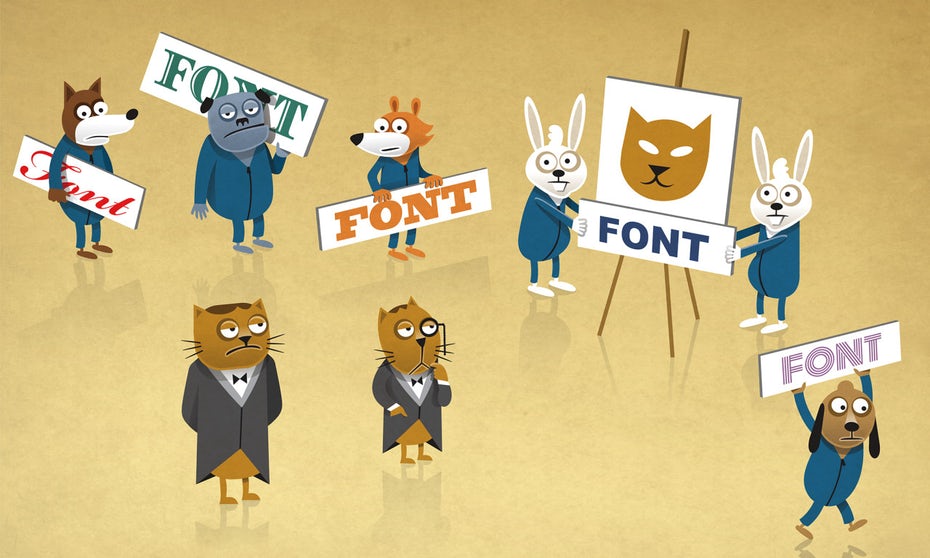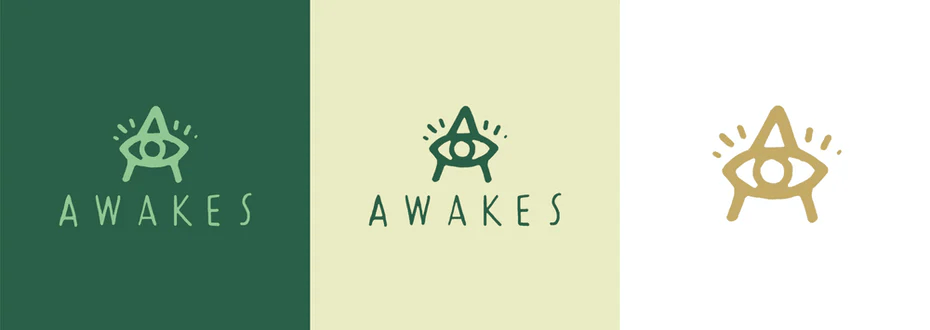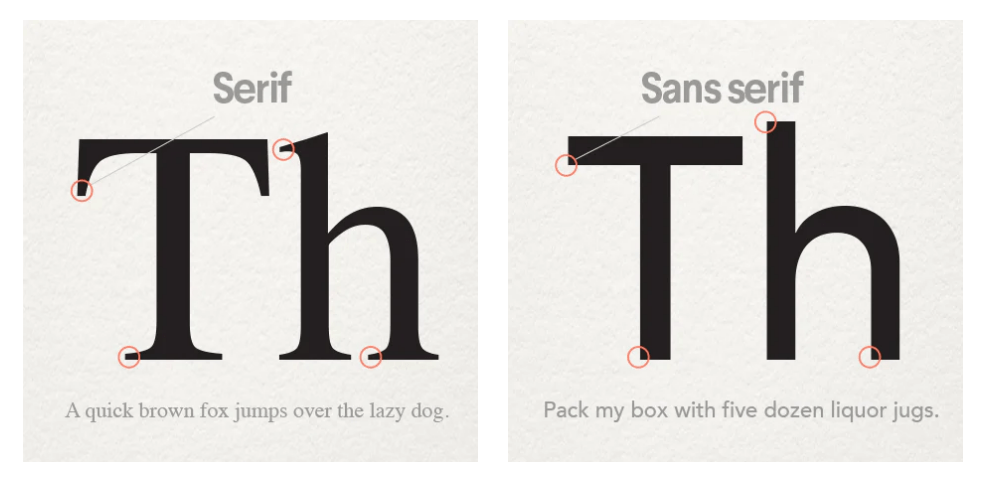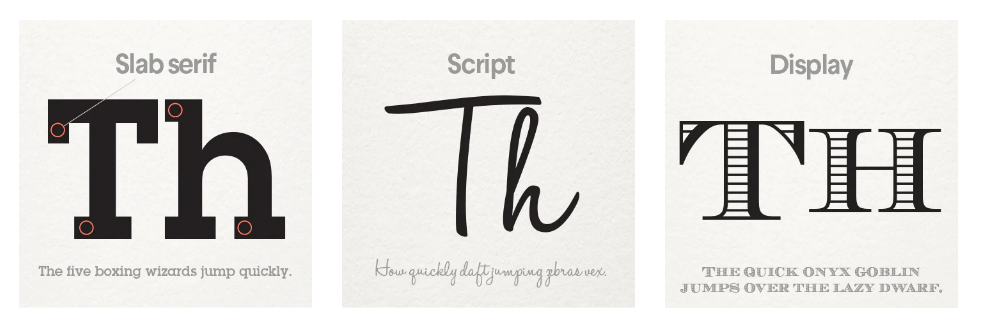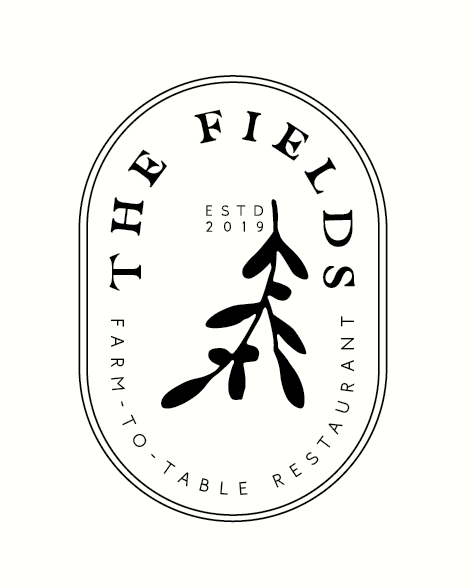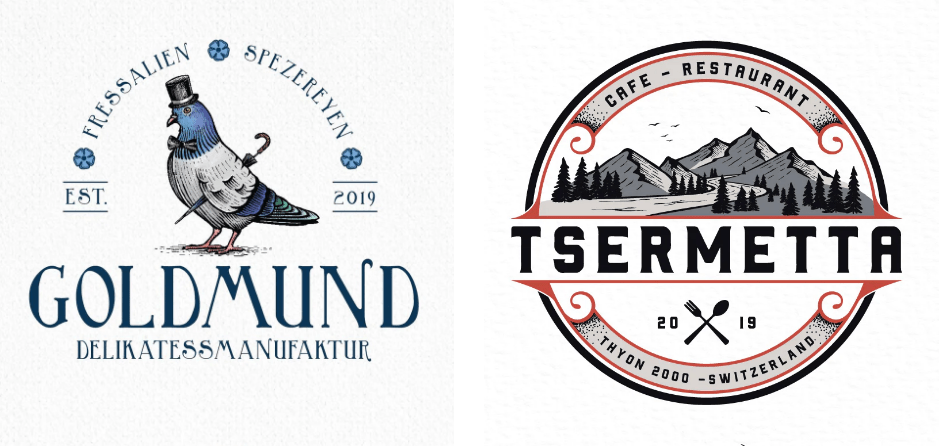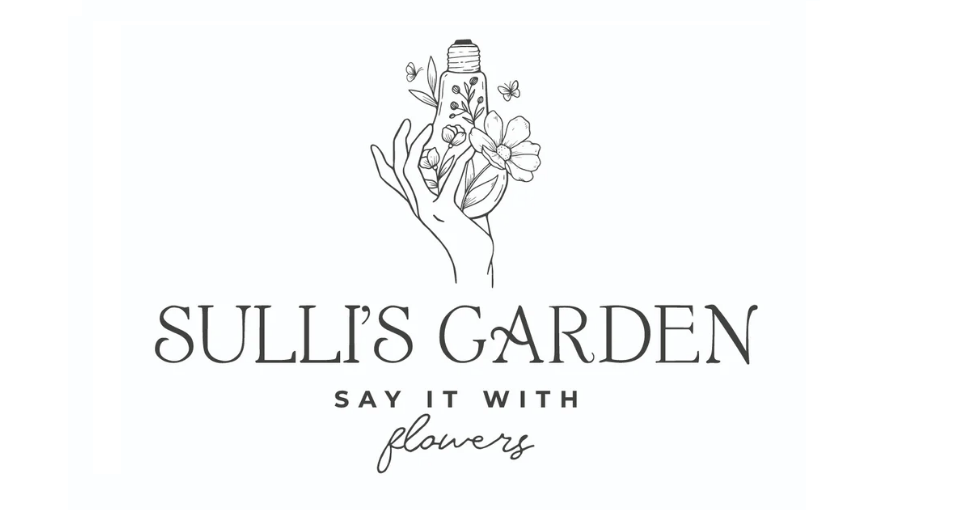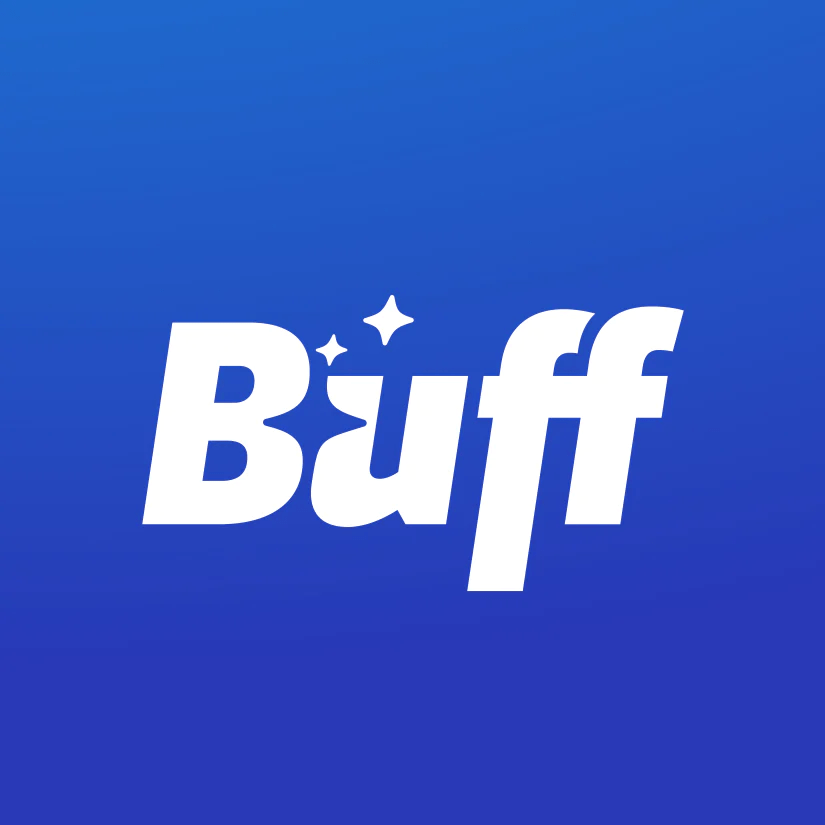
Khi nghĩ đến logo, thứ đầu tiên xuất hiện trong tâm trí bạn là gì? Phải chăng là những yếu tố  đồ hoạ hoặc hình ảnh nào đó? Liệu các designer nên chọn kiểu chữ có chân hay không chân, cứng rắn hay mềm mại cho những sản phẩm thiết kế của họ?
Để cho ra đời được một thành phẩm logo đúng nghĩa, một người designer không chỉ phải  thể hiện hình ảnh, thông điệp của thương hiệu vào trong một thiết kế đồ họa nhỏ bé, mà họ còn phải tìm ra những phông chữ phù hợp để truyền tải thông tin về thương hiệu một cách tốt nhất. Việc đó càng khiến các designer phải hao tâm tổn sức rất nhiều để tìm ra đâu mới là là font chữ “chân ái” của thương hiệu mà họ đang thiết kế.
Chọn font chữ như thế nào mới phù hợp với logo thương hiệu?
Điểm danh các loại font chữ cơ bản và mối liên kết của nó với cá tính thương hiệu
Trong thế giới của font chữ, bạn sẽ bắt gặp hàng triệu những loại font chữ khác nhau. Tuy nhiên mỗi loại font đều có những thuộc tính và bản tính riêng biệt. Nhưng bạn có biết font chữ như thế nào thì phù hợp với trang web, còn loại font ra sao thì phù hợp với tài liệu quảng cáo và các sản phẩm in, email, danh thiếp?
Các font chữ khác nhau sẽ sở hữu i những thuộc tính khác nhau và đại diện cho những tính cách riêng biệt. Logo và nét chữ trên đó phần nào sẽ giúp người nhìn hiểu được về tính chất của doanh nghiệp hoặc mặt hàng mà doanh nghiệp đó đang  kinh doanh. Điều đó đồng nghĩa với việc logo sẽ là nơi đầu tiên truyền tải thông điệp thương hiệu đến khách hàng. Do đó, cách font chữ được sử dụng trong việc thiết kế logo cực kỳ quan trọng, chúng cần được lựa chọn kỹ càng và mang tính lâu dài.
Tựu trung lại, chúng ta có những font chữ cơ bản và phổ biến sau đây, nhưng hãy đọc tiếp phần sau để hiểu sâu hơn mối liên hệ mà mỗi loại phông chữ sẽ gợi lên ở khách hàng tiềm năng.
– Serif: Sự cổ điển, sang trọng, truyền thống.
– Sans-Serif: Sự hiện đại, sạch sẽ, hơi hướng hình học, đơn giản.
– Slab Serifs: Sự cổ điển, mộc mạc, nam tính.
– Script: Sự tinh tế, nữ tính, có tính trang trí ứng dụng, thanh lịch.
– Handwritten: Dấu ấn cá nhân, giản dị, gần gũi.
– Display: Sự vui mắt, mới lạ
Độ dày nét chữ và khả năng ứng dụng
Để đánh giá một font chữ có phù hợp với thương hiệu hay không, ngoài yếu tố thẩm mỹ và sự kết nối với các tính cách như đã nêu trên, người thiết kế còn  phải xem xét đến độ dày của nét chữ và khả năng linh hoạt của chúng khi ứng dụng trên nhiều ấn phẩm khác nhau.
Khi đã chọn ra được  danh sách  các phông chữ phù hợp , bạn đã có thể thu hẹp phạm vi lựa chọn khi đã có các đặc điểm về phong cách và thuộc tính của thương hiệu . Hầu hết các font chữ đều đi theo một loạt biến thể về cách đi nét và độ dày nét, từ mảnh đến dày, từ bề mặt chữ có màu đến chữ chỉ có viền nét.
Thông thường những font chữ nét dày dặn có thể sẽ đẹp đối với thương hiệu có tên ngắn gọn, nhưng sẽ trông nặng nề và thô kệch khi áp dụng cho những cái tên dài hơn. Còn font chữ mảnh mai sẽ phù hợp trên những tấm biển quảng cáo cỡ đại, nhưng lại sẽ có thể “vô hình” trên một chiếc danh thiếp được in với kích cỡ nhỏ. Hơn nữa, nếu xét ở góc độ kết nối với tính cách, trong khi nét dày đại diện cho sự quyết đoán, mạnh mẽ thì nét mỏng lại biểu hiện sự tinh tế, nhẹ nhàng.
Nói tóm lại, nếu bạn muốn thiết kế một chiếc logo sang trọng, hãy cân nhắc những font chữ nét mảnh mang cảm giác tinh tế, trường hợp này nếu dùng phông chữ nét dày sẽ khiến thiết kế trở nên bảo thủ và nặng nề.
Bên cạnh đó, người thiết kế cũng có thể tạo điểm nhấn cho logo bằng việc phá cách với các font chữ vốn đã quen thuộc. Thậm chí, họ có thể kết hợp nhiều hơn một font trên cùng một chiếc logo như thiết kế của nhà hàng The Fields dưới đây. Sự kết hợp giữa nét chữ cổ điển, mềm mại phía trên với nét chữ dứt khoát, hiện đại phía dưới đã tạo nên cảm quan vô cùng hài hòa và thú vị.
Thiết kế logo của một nhà hàng với phông chữ serif viết tay. Minh họa bởi EWM Designs.
Trong thiết kế logo của nhà hàng The Fields, chữ “E” trong chữ “The Fields” được thể hiện bằng font Serifs chính là điểm nhấn khác biệt. Bên cạnh đó, mật độ xuất hiện vừa phải (chữ cái “E” chỉ xuất hiện hai lần trong logo) cũng là yếu tố gây thích thú cho người xem, nếu chữ “E” xuất hiện nhiều hơn hai lần có thể sẽ không còn gây được ấn tượng.
Tóm lại, trước khi lựa chọn font chữ cho thiết kế logo, hãy cân nhắc mọi khía cạnh liên quan đến thương hiệu. Nhờ vậy bạn mới có thể sáng tạo được một thiết kế vừa thỏa mãn khách hàng, vừa đạt được kỳ vọng của bản thân.
Sự tương hợp giữa font chữ và ngành hàng
Khi cân nhắc lựa chọn font chữ cho logo, điều quan trọng không chỉ là bạn muốn logo trông như thế nào mà còn là bạn muốn nó  được cảm nhận như thế nào. Liệu logo có cần biểu đạt một hàm ý lịch sử, hay chỉ cần mang đến cảm giác thích thú và hiện đại? Điều này cần bạn phải có hiểu biết thực tế và cực kỳ sâu sắc về ngành lẫn thương hiệu đó.
Kiểu chữ gợi cảm giác chân chất, mộc mạc có thể phù hợp với logo của một cửa hàng cơ khí nhưng sẽ hoàn toàn lạc lõng trên logo của một công ty phần mềm. Một kiểu chữ tạo sự rung cảm thô mộc có thể phù hợp với cửa hàng cơ khí nhưng sẽ trở nên lạc lõng trên logo của công ty phần mềm. Vì vậy trước khi đặt bút phác thảo một logo bất kì, người thiết kế cần nghiên cứu những mong đợi, sở thích, tính cách chung của người tiêu dùng trong ngành hàng đó để tìm kiểu chữ phù hợp.
Chọn font chữ như thế nào mới phù hợp với logo thương hiệu?
Bên cạnh đó, hãy cẩn thận với những font chữ quá phổ biến, ví dụ như kiểu chữ Serifs (không chân) theo dạng cổ điển vì nó đã quá “nhẵn mặt” với các hãng bia đến nỗi chúng chẳng còn gì mới lạ với người tiêu dùng. Còn đối với ngành công nghệ, phông chữ Sans-Serifs (có chân) cũng khiến cho các logo trở nên nhạt nhòa trong hàng loạt thiết kế tương tự.
Chính vì thế mà đôi khi sử dụng những font chữ đặc trưng, dễ nhận biết của ngành lại mang tác dụng phụ, khiến logo của  bạn trở nên chìm nghỉm giữa các đối thủ khác. Do đó, kết quả cuối cùng của việc thiết kế logo cần đảm bảo thể hiện được tinh thần của ngành, nhưng đồng thời cũng cần tươi mới và nổi bật hơn các đối thủ cạnh tranh.
Cách kết hợp nhiều font chữ trong một logo
Chọn font chữ như thế nào mới phù hợp với logo thương hiệu?
Đừng bao giờ dùng nhiều hơn hai hoặc ba font chữ khác nhau trong cùng một logo. Bạn cần biết rằng  bố cục thiết kế phải có hệ thống phân cấp thị giác rõ ràng, để giúp cho người xem có thể nhận biết được thứ tự quan trọng của các hình ảnh, thông tin được trình bày trên bản thiết kế.
Thông thường, logo là sự kết hợp giữa văn bản và biểu tượng, đôi khi sẽ bao gồm cả năm thành lập, khẩu hiệu hoặc địa điểm kinh doanh. Vì thế, tên thương hiệu sẽ là phần thiết kế cần được nổi bật nhất bằng một font chữ riêng biệt, chiếm diện tích thiết kế lớn nhất và nằm ở bậc cao nhất của hệ thống phân cấp thị giác. Những phần còn lại như năm thành lập, khẩu hiệu, địa điểm cần được thiết kế trong một font chữ khác, kiểu dáng gọn gàng và kích thước nhỏ hơn, ví dụ như Sans-Serifs hay Serifs chẳng hạn.
Nếu logo của bạn bao gồm hình ảnh đồ hoạ, hãy cân nhắc làm sao để phần hình và phần chữ có thể bổ sung cho nhau. Cụ thể hơn, độ dày/mỏng của các nét vẽ ở phần hình phải ăn nhập với độ dày/mỏng của nét chữ như thiết kế dưới đây.
Chọn font chữ như thế nào mới phù hợp với logo thương hiệu?
Một logo thương hiệu khiến khách hàng nhớ lâu không nhất thiết phải là một thiết kế cao siêu, phức tạp hay chứa nhiều thông tin. Đôi khi, sự đơn giản lại giúp cho thương hiệu trở nên ấn tượng.
Logo của các ông lớn như Google, Visa hay Facebook đều bỏ qua các yếu tố đồ hoạ và chỉ tập trung làm nổi bật tên thương hiệu bằng cách sử dụng font chữ tối giản nhưng đầy ấn tượng. Một số thương hiệu nhỏ cũng áp dụng cách làm này trong thiết kế logo của họ.
Chọn font chữ như thế nào mới phù hợp với logo thương hiệu?
Tóm lại khi thiết kế logo, hãy xác định rõ ràng logo của bạn thuộc dạng hình hay chữ. Nếu là logo dạng hình, hãy khiến nó gọn gàng và đơn giản. Nếu logo dạng chữ, hãy lựa chọn font chữ phù hợp với đặc tính của thương hiệu.
Những điều cần lưu ý về các vấn đề về kỹ thuật
Để có chất lượng nhận diện logo cao nhất, đặc biệt là nhìn từ khoảng cách xa, người thiết kế cần cân nhắc sử dụng các phông chữ đơn giản và có khoảng trắng giữa các chữ cái. Sans-Serif là phông chữ đáp ứng hoàn hảo các điều kiện này.
Tiếp theo, nếu logo được sử dụng chủ yếu trên các nền tảng công nghệ số, hãy cân nhắc lựa chọn những phông chữ được tối ưu hoá cho website và cho những hình ảnh có kích thước nhỏ. Điều này có nghĩa, logo có thể hiển thị một cách rõ ràng cả trên màn hình lớn lẫn giao diện điện thoại với kích thước hiển thị nhỏ hơn nhiều.
Chọn font chữ như thế nào mới phù hợp với logo thương hiệu?
Bên cạnh đó, đừng quên cân nhắc thiết kế logo trên các nền màu sắc khác nhau, bạn có thể thử từ dạng nền đơn sắc cho đến dạng nền hòa trộn nhiều màu như gradient.
Chọn font chữ như thế nào mới phù hợp với logo thương hiệu?
Đảm bảo rằng font chữ vẫn có thể nổi bật với nhiều màu sắc khác nhau.
Và điều lưu ý cuối cùng dành cho bạn. Nếu bạn tải xuống hoặc sử dụng bất kỳ font chữ nào không rõ ràng về vấn đề bản quyền, bạn hãy cẩn trọng khi dùng font chữ đó để thiết kế cho các doanh nghiệp, vì một số font chữ sẽ chỉ được cấp phép cho mục đích cá nhân.
Ngoài ra, bạn cũng mua hoặc tự sáng tạo những font chữ được thiết kế độc quyền cho thương hiệu, điều đó sẽ giúp các thiết kế logo của bạn trở nên độc nhất vô nhị và tạo lợi thế giữa hàng loạt các thiết kế logo tương tự nhau.
Chọn font chữ như thế nào mới phù hợp với logo thương hiệu?
Một ví dụ hay về logo có font chữ được thiết kế độc quyền được thực hiện bởi nevergohungry.
Chốt lại, việc lựa chọn font chữ cho logo hoặc bộ nhận diện thương hiệu luôn là một vấn đề quan trọng mà các designer phải cân trong bất kỳ thiết kế hay dự án nào. Bạn không thể chọn một font chữ dựa vào bản năng hoặc sở thích cá nhân mà bạn phải nghiên cứu và đặt mình vào vị trí là vị khách hàng của thương hiệu trong tương lai.